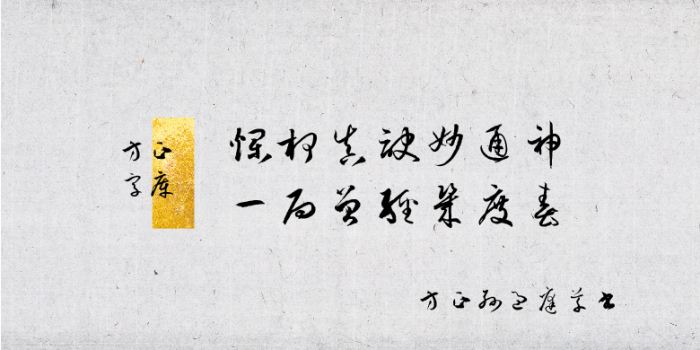
方正孫過庭草書由方正字庫張嘉杰設(shè)計師出品的藝術(shù)字體,該字字體流暢婉轉(zhuǎn)而又雋拔剛斷,富于變化;剛?cè)嵯酀w動輕繼,意趣盎然,適合應用于藝術(shù)設(shè)計、平面宣傳設(shè)計、網(wǎng)頁設(shè)計,書法等領(lǐng)域。
以孫過庭草書墨跡《書譜》為主要臨創(chuàng)開發(fā)依據(jù)。字體流暢婉轉(zhuǎn)而又雋拔剛斷,富于變化;剛?cè)嵯酀?,飛動輕繼,意趣盎然。。